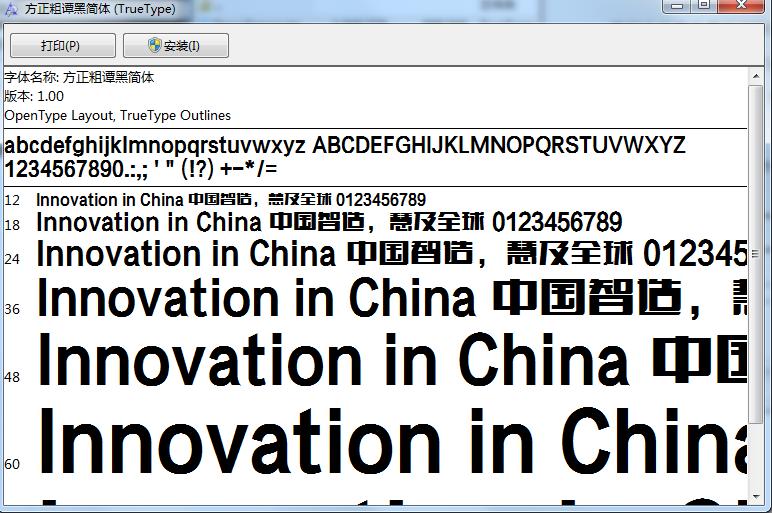
软件介绍 软件标签: fzcthjwgb10 字体 fzcthjw gb10字体的别名又叫方正粗谭黑简体,这款字体使用非常广泛,字形宽扁,线条比较粗,看起来非常霸气,喜欢的朋友欢迎来绿色资源网下载哦!fzcthjw gb10字体安装使用方法方法一:控制面板/字体/文件/安装新字体;方法二:直接将字体复制到C:\WINDOWS\Fonts。fzcthjw gb10字体简介方正粗谭黑简体下载,本字体包括符号及英文和数字共9000多个字,耗时2年一笔一划十分苛刻和精心完成。因为初衷是用品牌设计中的中文字体设计,在单字和细节雕琢过多,不能兼顾整体,所以本字体不宜很多字成排使用。 软件截图 上一张下一张(1 / 1) 安装详细截图 其他版本下载 标题 大小 更新日期 下载 下载地址 电脑版 字体fzcthjw gb1 0免费 点击报错 软件无法下载或下载后无法使用,请点击报错,谢谢! 关闭报错反馈 请描述您所遇到的错误,我们将尽快予以修正,谢谢! *必填项,请输入内容 本类最新 dreamweaver字体库 首尔南山体字体 v1.06 官方版 潮字社风云简ttf 潮字社凌渡鲲鹏简体字体 潮字社曾玉波手书简字体 微博慧心字体 相关文章 Photoshop字体安装使用方法和技巧 如何解决“无法新增字体”问题 Win 7系统安装字体方法 网页字体大小设置方法 怎么改网页字体大小 在Linux系统中安装字体的几种方法 windows7字体显示问题:打开某些程序的时候显示的是乱码 用户评论 热门评论 最新评论 发表评论 查看所有评论(0) 昵称: 请不要评论无意义或脏话,我们所有评论会有人工审核. 字数: 0/500 (您的评论需要经过审核才能显示)